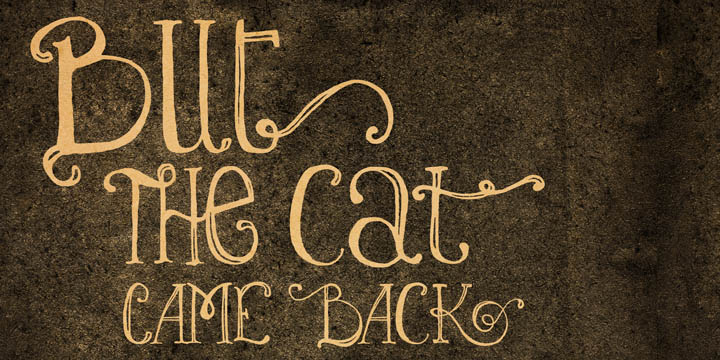
Font iCiel Lady Rene Việt Hóa
Tác giả: iCiel
Việt hóa: Fontchuviethoa.com
Bộ Font: iCiel
Phân loại: Độc đáo
Kiểu chữ: Có chân
Độ dày: Regular
Font iCiel Lady Rene Việt Hóa Miễn Phí
Font iCiel Lady Rene là một Font iCiel. Đây là một kiểu chữ mang phong cách cổ điển và thanh lịch, được yêu thích bởi sự tinh tế và sự mềm mại trong từng nét chữ. Với đặc điểm là các đường nét uốn lượn tinh xảo, font chữ này thường được sử dụng trong các dự án thiết kế có tính chất sang trọng như thiệp mời, tiêu đề hay các ấn phẩm nghệ thuật. Font iCiel Lady Rene không chỉ là sự lựa chọn lý tưởng cho những ai muốn tạo điểm nhấn về mặt thị giác, mà còn giúp tăng cường cảm giác chuyên nghiệp và sáng tạo cho thiết kế của bạn.